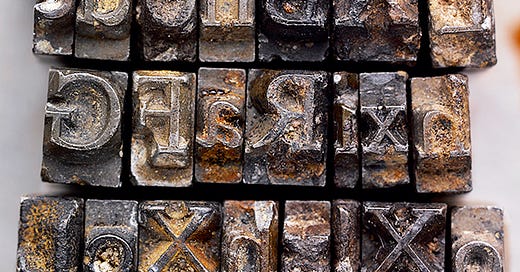
Tipo Aquilo #78 – O tempo que as coisas duram
Uma carta sobre tempo, longevidade e preservação de fontes
Esta edição tem um formato diferente. A comunidade de escritores de newsletters está fazendo a segunda edição do troca-troca de cartas entre escritores, e o Tipo Aquilo desta semana é uma carta para uma das pessoas da comunidade. Mais especificamente, a
, escritora, publicitária e produtora da newsletter. Mas não precisam ficar acanhados, achando que estão lendo conversa dos outros; apesar de ser uma carta, a ideia é pegar um texto escrito pela Bruna e continuar falando de tipografia com base nesse texto. Então, fique à vontade e aproveite esta penúltima edição do ano.—
Olá, Bruna. Tudo bem com você? Espero que 2023 tenha sido um ano gentil contigo, e que 2024 seja generoso para você e seus planos, desejos e amores. Uma coisa legal de ter contato com escritores é ver várias formas de contar sobre sentimentos e acontecimentos, e sentir que vários trechos e até textos inteiros dizem muito sobre minha vida no momento. “Coisa de artista”, digo, num dos raros momentos em que me entendo como uma pessoa criativa. Enfim, é uma questão de momento, de alinhar as coisas certas no tempo certo.
Aliás, o tempo é um assunto que tem consumido meus pensamentos há algum… tempo (rá!). Especialmente, desde quando me mudei para o Canadá e alguns planos não aconteceram do jeito que eu queria, ou no tempo que eu queria. Por isso, me senti contemplado e confortado pelo seu texto sobre o tempo que as coisas levam. Em retribuição, achei uma boa ideia trazer um assunto que eu quero falar no Tipo Aquilo há tempos e, se você não se importar, colocar meus leitores também para pensar no tempo das letras e, mais precisamente, das fontes: quanto tempo dura uma fonte?
Antes de deixar o Brasil, eu ganhei de presente um fac-símile de uma página da famosa Bíblia de 42 linhas, que teve em torno de 150 a 180 exemplares impressos entre 1450 e 1455. É possível adquirir um fac-símile desses no Gutenberg Museum, em Mainz, onde também encontram-se equipamentos e réplicas utilizadas por Gutenberg e outros impressores ao longo dos séculos para compor clichês, imprimir e encadernar publicações. Ainda quero visitar, mesmo sabendo que nada ali foi realmente usado por Gutenberg. Os equipamentos e tipos criados por Johannes e seu assistente Peter Schöffer existem apenas em relatos, que sabemos por outros impressores e pelo litígio em que o agiota banqueiro Johann Fust tomou seus pertences.
É curioso que os equipamentos de Gutenberg não tenham resistido ao tempo. Cita-se comumente o impressor alemão como inventor da tipografia, mas na verdade, os tipos móveis precedem Gutenberg. Há evidências do uso de pequenos blocos de cerâmica, metal e madeira na China desde o séc. X. Temos também tipos móveis coreanos do séc. XIV guardados até hoje; sendo assim, sabemos que é possível preservar tipos móveis por, no mínimo, quase 800 anos. Só que isso tende a ser mais exceção do que regra: o uso regular dos tipos em oficinas de impressão fazia com que as formas das letras se desgastassem, degradando a qualidade dos impressos após alguns anos. É possível visitar algumas oficinas que mantêm viva a tradição da tipografia manual, ver e até montar clichês, enfileirando letras lado a lado formando palavras, frases e sentenças, como os primeiros impressores da Europa faziam há mais de 500 anos. Os tipos podem não ter a mesma nitidez e os detalhes de quando saíram da caixa, mas ainda carregam uma manualidade que enche os olhos de alegria.
Aliás, Bruna, acho legal citar o caso da Doves, antes de passar para outros sistemas de composição tipográfica. Emery Walker encomendou, em 1900, tipos para sua gráfica tão fiéis quanto possível aos tipos de 1492 de Nicolas Jenson, e usou estes tipos entre 1900 e 1917 com seu sócio Thomas Cobden-Sanderson. Por divergências internas e dificuldades financeiras, Walker preferiu jogar sua fonte no fundo do rio a entregá-las para seu sócio, restando apenas os impressos reverenciados por anos entre artistas gráficos. Contudo, em 2014, os tipos da Doves Press foram resgatados do fundo do Tâmisa; é impossível utilizá-los para imprimir novamente, mas se por 100 anos os tipos pareciam perdidos para sempre, hoje é possível estudá-los e compará-los às fontes digitais baseadas em seus impressos.
Falar de tempo e de quanto dura uma fonte torna-se mais complexo quando falamos dos sistemas de composição a quente, como o Monotipo e o Linotipo, usados ostensivamente até os anos 1970. Ao invés de montar blocos de letras, essas máquinas carregavam suas próprias matrizes e, usando-as como molde para as letras, fundiam metal e criavam linhas inteiras em segundos. Essas linhas, empilhadas e presas umas às outras, formavam os clichês usados para imprimir jornais e revistas e, depois, voltavam ao estado de metal fundido para virarem novas linhas, reiniciando o ciclo. Com a rapidez que esses periódicos exigiam, era questão de dias ou horas para que a forma sólida das letras na impressão já não existisse mais, adquirido novas configurações com o tempo. Nada se perde, tudo se transforma.
De todos os sistemas de composição tipográfica, o tempo talvez tenha sido mais irônico com a fotocomposição, usada dos anos 1950 a 1980. Era um sistema complexo que, resumidamente, projetava letras com luz em um anteparo, como um filme fotográfico. Isso dava flexibilidade para usar letras em diferentes dimensões, ao invés de tamanhos fixos como na impressão com metal, e dezenas de matrizes das máquinas de fotocomposição encontram-se preservadas até hoje. A gente ouve falar pouco desse sistema porque ele não resistiu ao tempo dos computadores e sistemas digitais, que mostraram-se mais capazes e poderosos para criar impressos e publicações. De forma geral, foi o sistema de composição que por menos tempo vingou na indústria. Máquinas e matrizes de fotoletras, hoje, são coisa de museu.
Quando falamos do tempo dos computadores, Bruna, uma grande preocupação que temos é relativa a como preservamos informações. Não sei se você teve problemas com backup de algo importante, como todo mundo já teve nos momentos mais cruciais. No entanto, imagine o desafio de manter preservado e acessível, por exemplo, um jogo distribuído digitalmente para um video-game que não é fabricado há uma década. Difícil, não? Na tipografia digital, temos formatos como o PostScript, que não tem mais suporte oficial e, fora de um ambiente de emulação de sistemas antigos ou de scripts de conversão para formatos atuais, não tem mais uso. É factível que, em aproximadamente 50 anos de tipografia digital, já tenhamos fontes perdidas para sempre em arquivos irreconhecíveis de sistemas legados.
Só que a tipografia digital, Bruna, abriu caminho para que mais type designers em todo o mundo crie fontes baseadas em impressos e tipos antigos. Eu sou um exemplo, com o meu trabalho de recriação da Grotesca Reforma da antiga fundadora brasileira Funtimod. Aliás, o resgate tipográfico é uma prática de type designers amadores e profissionais para aprender o bê-a-bá do design de tipos e preservar, no mínimo, o espírito das letras usadas há dezenas ou centenas de anos. Existem aplicativos de criação de fontes dos mais simples aos mais completos, para diferentes estágios de aprendizagem; assim como também existem dezenas de fontes e letterings antigos, melhor ou pior documentados, que estão apenas à espera de algum designer interessado em reproduzir suas formas de letras.